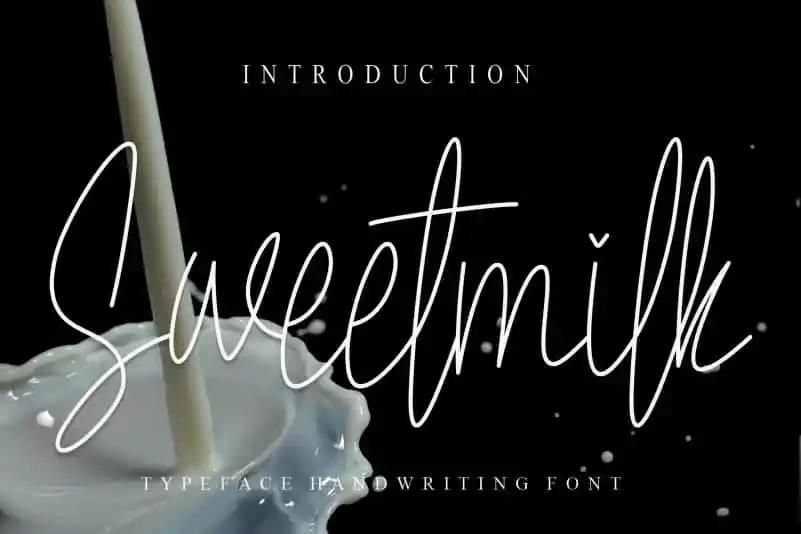
Sweetmilk Handwritten Font – Download Grátis
A Sweetmilk Handwritten Font é uma escolha perfeita para quem busca um toque único e natural em seu design. Inspirada no estilo delicado das letras à mão, essa fonte oferece uma experiência visual única que combina harmonicamente com textos legíveis e elegantes. Ela foi criada pelo designer creativeletter e sua característica principal é a transição suave entre linhas levemente tortas e pontadas finas, proporcionando um aspecto natural que se destaca em qualquer texto. Seja para design gráfico, publicidade ou arte digital, essa fonte entrega um toque de personalização que certamente impressionará seus destinatários. Ela é perfeita para manusear textos legíveis e encantadores sem comprometer a expressão visual única do estilo à mão.